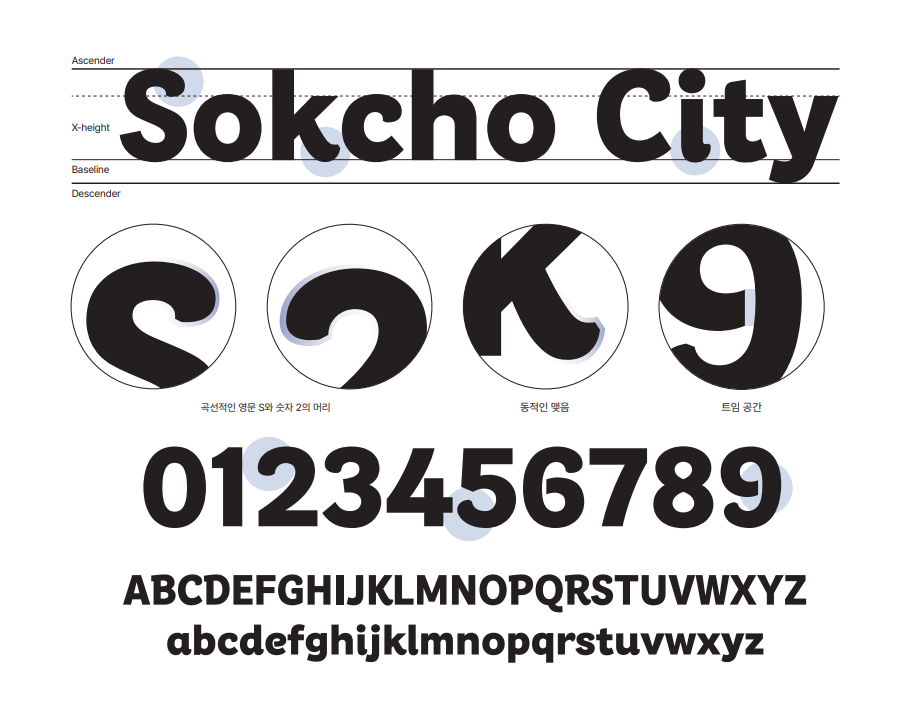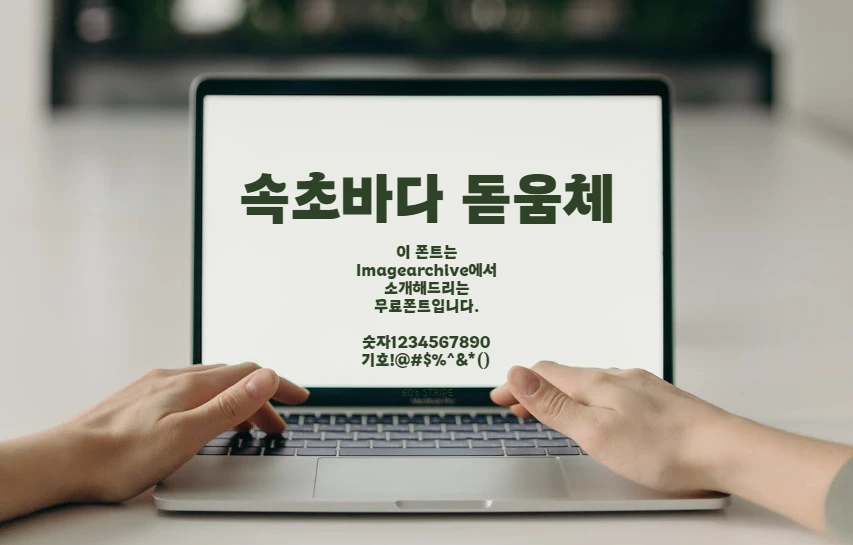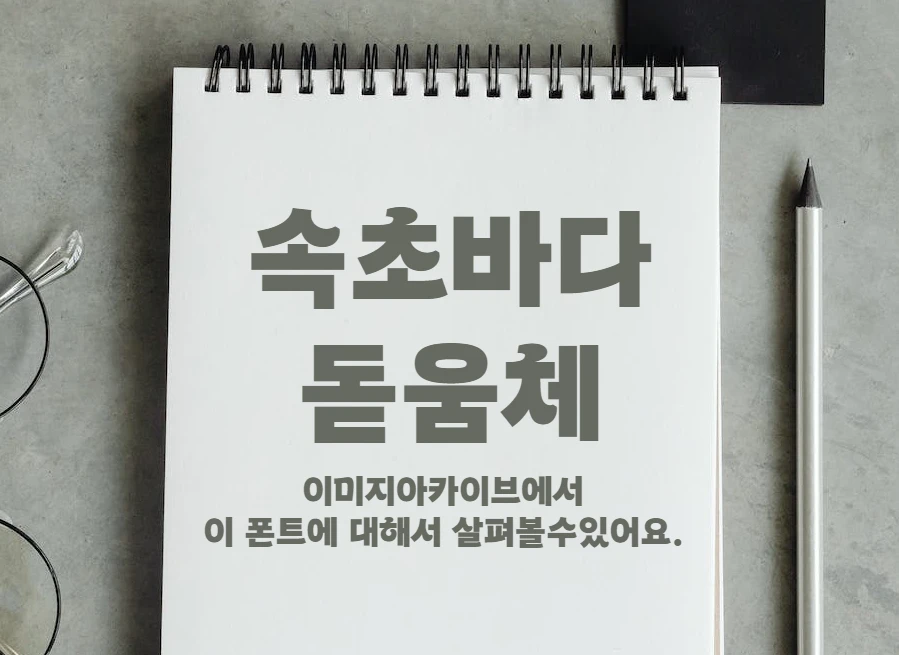
속초바다 돋움체
속초시의 자연과 미래 발전을 상징적으로 표현하였고, 제목용 서체로 주목성 높은 두께로 설계되어서 타이틀폰트로 좋습니다. ‘ㅅ, ㅈ, ㅊ’ 꼴의 내리점을 역동적인 형태로 표현하여 활기찬 분위기를 가진 서체입니다. 파도의 모습을 형상화한 모습인것 같아서 더욱 매력이 있는 폰트로 보여집니다.
14포인트 이상의 크기로 사용했을 때 서체의 아이덴티티가 더욱 명확하게 표현되며, 14포인트 이하의 크리로 사용 시 출력 매체의 상태에 따라 가독성이 떨어질 수 있습니다. 그러므로 되도록 크게 작성된 포스터나 디자인할 때 사용하기 좋으며 문서의 본문이나 작은 글씨를 적용해야하는 곳에는 사용하지 않는것이 좋을 수 있습니다.